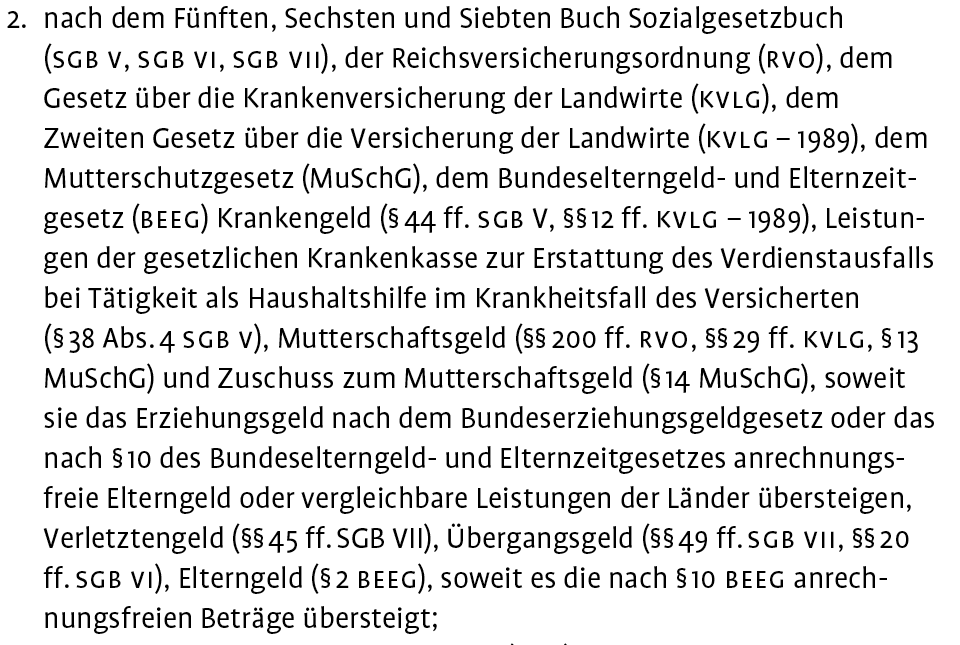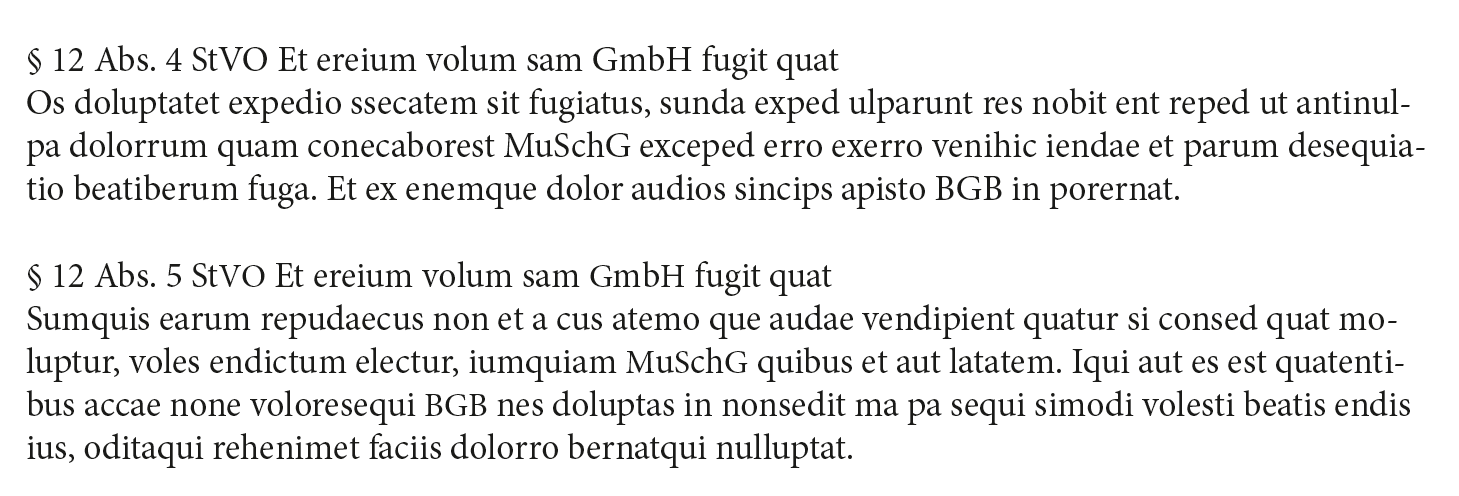
für ein Seminar an der FH setze ich gerade die BAföG-Formulare neu. Da im Kleingedruckten sehr viele Abkürzungen à la BGB, SGB oder MuSchG vorkommen würde ich diese gerne in Kapitälchen setzen. Meine Frage ist nun, was mache ich mit Abkürzugen wie MuSchG (Mutterschutzgesetz) die ja eigentlich Groß- und Kleinbuchstaben benötigen? Lasse ich diese in gemischter Schreibweise stehen und setze die anderen in Kapitälchen? Ich stehe gerade auf dem Schlauch. :-?
also ich würde die Abkürzungen gemischter Schreibweise im ganz normalen Schriftschnitt bestehen lassen und sie nicht aus Kapitälchen setzen. Dass man bei Abkürzungen, die aus reinen Versalien bestehen, auf Kapitälchen zurückgreift (oder die Versalien kleiner setzt als den restlichen Text) ist doch darin begründet, dass man ihr Hervorstechen aus dem Fließtext vermeiden will. Bei gemischt geschriebenen Abkürzungen entsteht dieses Problem aber gar nicht, weil sie sich optisch unauffällig und damit harmonisch in den Fließtextkontext einfügen.
die Antwort leuchtet natürlich ein. Ich habe mich allerdings gefragt ob es in dieser Art und Weise evtl. inkonsequent aussieht. Sinn macht es aber so wie du es beschrieben hast. :-D
Probier es doch einfach mal aus. So was lässt sich meist erst richtig beurteilen, wenn man es tatsächlich mit eigenen Augen und am besten ausgedruckt auf Papier gesehen hat (das geht mir jedenfalls immer so). Wenn Du alternativ die Abkürzungen insgesamt (versal und gemischt) vom restlichen Fließtext abheben willst, statt sie unsichtbar zu machen, dann bliebe Dir immer noch die Option, sie durch einen kursiven oder einen fetteren Schriftschnitt zu betonen. :-)
Ich glaube (ohne es zu wissen), dass jeder dahergelaufene und gewöhnliche Rechtsverdreher, der aus seiner lethargischen Gewohnheit gerissen wird, Protest geben wird, wenn er nicht sein gewohntes MuSchuGeAnwVoLE (Mutterschutzgesetzanwendungsverordungleitfadenempfehlung oder so) Revision 4.2 mit Kommentaren zur Auslegung von Richter Gnadenlos und Konsorten vorfindet. Wenn du aus GmbH „GMBH“ oder „GmbH [small caps]“ in einem derart offiziellen Umfeld einsetzt, holst du dir nur Probleme von bornierten Bürohengsten / Sesselfurzern ins Haus. Setze es klassisch, ordentlich, sauber und fertig. Das ist auch eine Herausforderung. Keine Experimente hier. Ergo keine Probleme mit deinem Prof. Kaum jemand außerhalb dieses Forums würde deine Ideen und Anstrengungen würdigen, so gut sie auch gemeint seien. Blumentöpfe gewinnt man woanders. Vielleicht zielt die Aufgabe ja auch darauf ab, um zu checken, ob du nach Vorgabe arbeiten kannst. Mit Sicherheit hast du viele tolle Ideen, die wären jedoch an anderer Stelle viel effektiver als auf einem Behördenformular.
hm, Kais Hinweise sind sicher nicht falsch, aber halt nur Standard, bei dem man sich nicht mit der Materie beschäftigen muss. Kann ja auch eine Herangehensweise sein.
Ich würde es eher mit Kathrins Meinung halten und es einfach mal ausprobieren. Je nach verwendeter Schrift und je nach Größenverhältnis Kapitalen zu Gemeinen kann das ganz gut aussehen, wenn in gemischten Abkürzungen die Versalien verkleinert werden.
Hier ein schnelles Beispiel mit 93 (unten) und 100 (oben) Prozent:
Ich glaube (ohne es zu wissen), dass jeder dahergelaufene und gewöhnliche Rechtsverdreher, der aus seiner lethargischen Gewohnheit gerissen wird, Protest geben wird, wenn er nicht sein gewohntes MuSchuGeAnwVoLE (Mutterschutzgesetzanwendungsverordungleitfadenempfehlung oder so) Revision 4.2 mit Kommentaren zur Auslegung von Richter Gnadenlos und Konsorten vorfindet. Wenn du aus GmbH „GMBH“ oder „GmbH [small caps]“ in einem derart offiziellen Umfeld einsetzt, holst du dir nur Probleme von bornierten Bürohengsten / Sesselfurzern ins Haus. Setze es klassisch, ordentlich, sauber und fertig. Das ist auch eine Herausforderung. Keine Experimente hier. Ergo keine Probleme mit deinem Prof. Kaum jemand außerhalb dieses Forums würde deine Ideen und Anstrengungen würdigen, so gut sie auch gemeint seien. Blumentöpfe gewinnt man woanders. Vielleicht zielt die Aufgabe ja auch darauf ab, um zu checken, ob du nach Vorgabe arbeiten kannst. Mit Sicherheit hast du viele tolle Ideen, die wären jedoch an anderer Stelle viel effektiver als auf einem Behördenformular.
Ich glaube, da hast Du mich falsch verstanden. Ich habe nicht gemeint, dass gemischte Abkürzungen in Versalien gesetzt werden sollen, sondern, dass ich die Versalien-Abkürzungen in Kapitälchen setzen würde und die gemischten Abkürzungen im normalen Schriftschnitt belassen würde – also gemischt.
Um mal zu zeigen wie es momentan aussieht, hier ein Screenshot.
Edit: Ich sehe gerade ich habe noch eine Abkürzung übersehen – ist bereits korrigiert.
hmmm, wenn ich mir das jetzt so anschaue, dann frage ich mich, ob das Setzen der Versal-Abkürzungen in Kapitälchen durch die zusätzliche Verwendung von Klammern nicht ein bisschen sehr unruhig aussieht. Bei Deinen Schilderungen hatte ich immer angenommen, dass die Abkürzungen einfach so im Fließtext mitlaufen sollen. Ich schätze, der Eindruck wäre ein bisschen ruhiger, wenn man statt der Kapitälchen nur leicht verkleinerte Versalien einsetzt. Was meinst Du?
Ich glaube, da hast Du mich falsch verstanden. Ich habe nicht gemeint, dass gemischte Abkürzungen in Versalien gesetzt werden sollen, sondern, dass ich die Versalien-Abkürzungen in Kapitälchen setzen würde und die gemischten Abkürzungen im normalen Schriftschnitt belassen würde – also gemischt.
Stimmt. Ich hab’s wohl zuerst nicht kapiert. Ich finde die Idee, so etwas überhaupt machen zu wollen, äußerst riskant. Bei Bankleitzahlen – also bei den drei Glyphen BLZ war das mal Usus, sie in Caps zu setzen; aber im gemischten Umfeld holt man sich Probleme ins Haus. Einige der Small-Caps sind nämlich kaum von deren Gemeinen zu unterscheiden, was zu Problemen führen kann. Das betrifft z.B. C ,O, S, V, W, X, Z. Darüberhinaus verstehe ich den gestalterischen Ansatz nicht; was soll das überhaupt bringen? Die Lesbarkeit wird nicht verbessert und es sieht *imho* auch nicht besser aus. </kai> Ich hab das mal probiert (TheSerif):
Ich habe die Profile eigentlich immer als gut lesbar empfunden. Außerdem ist sie sehr platzsparend, was in einem Formular ja meist von Vorteil ist. Der hier gezeigte Teil ist aus dem Anhang in dem einzelne Punkte noch mal erklärt sind (es ist also nicht überall so viel Fließtext).
Da ich eigentlich mit einer Schrift auskommen wollte, habe noch an die FF Parable gedacht.
Habt ihr denn evtl. einen Schrift-Vorschlag, der eurer Meinung nach besser geeignet wäre?